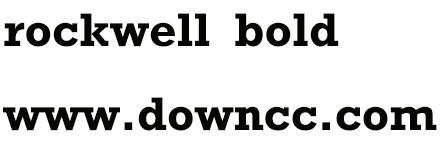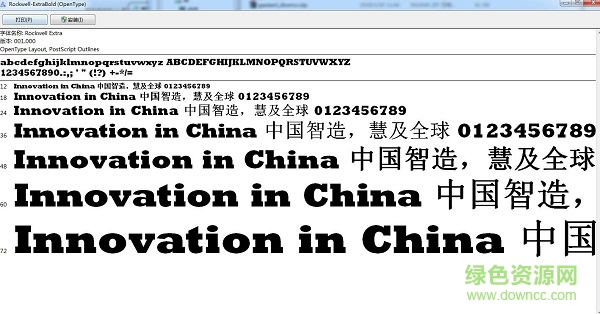
rockwell extra bold字體
rockwell extra bold字體和rockwell bold字體是本站為大家搜集的兩款經(jīng)典粗襯線(xiàn)字體,又稱(chēng)埃及體,線(xiàn)條粗,結(jié)構(gòu)嚴(yán)謹(jǐn),適用范圍發(fā)錯(cuò)了廣泛,需要這款字體的小伙伴快來(lái)本站免費(fèi)下載吧!
襯線(xiàn)字體的由來(lái)
「襯線(xiàn)」指的是字形筆畫(huà)在首位的裝飾和筆畫(huà)的粗細(xì)不同,所以「襯線(xiàn)」又被稱(chēng)為「字腳」這種裝飾線(xiàn)的筆畫(huà)設(shè)計(jì)多認(rèn)為來(lái)源于古羅馬紀(jì)念碑上的拉丁字母,1968 年 《The Origin of the Serif》中提到羅馬字母最初被雕刻到石碑上之前,要先用方頭筆刷寫(xiě)好樣子,再照樣雕鑿。由于直接用方頭筆刷書(shū)寫(xiě)會(huì)導(dǎo)致筆畫(huà)的起始和結(jié)尾出現(xiàn)毛糙,所以在筆畫(huà)開(kāi)始、結(jié)束和轉(zhuǎn)角的時(shí)候增加了收尾的筆畫(huà),也就自然形成了襯線(xiàn)。